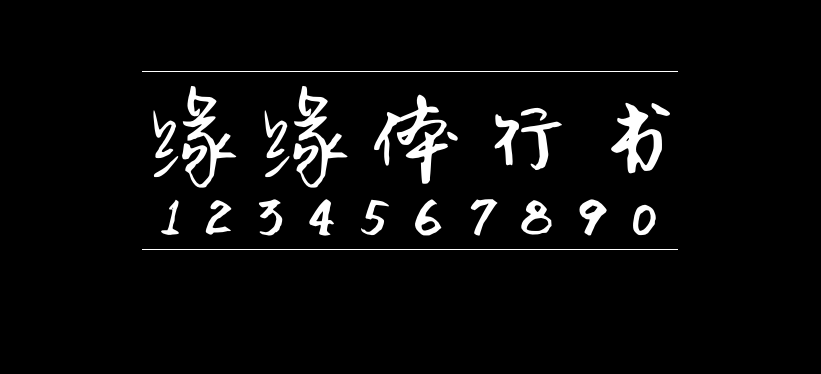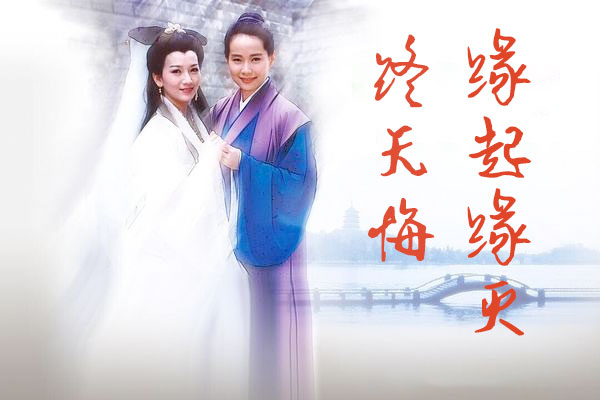
缘缘体行书
缘缘体行书(缘缘体行书GB2312、YUANYUANXSGB2312)作者是中国大陆的张缘缘。作者不仅人美,字也写得很美,由广西霁云轩字体工作室制作成字体文件分享给大家使用。这是一款适用于艺术设计方面的手写字体,字型十分漂亮。延续了行书的行云流水,添加了自己的特色,潇洒自如,简单大方,看上去很整齐,无拘无束,适用于广告设计、装潢设计、视觉设计等。
该字体支持的6763个常用字符,简体中文基本不缺字,繁体则相对少些。